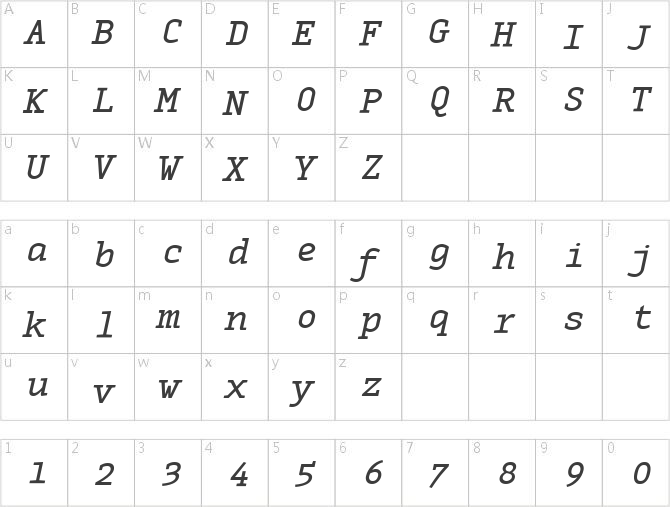
MonoxSerifRegularItalic
MonoxSerifRegularItalic介绍
MonoxSerifRegularItalic字体字库是一款让人赏心悦目、百看不厌的英文字体,适合各类广告和产品包装设计应用,字体大小0.04MB,格式为ttf字体,上传用户是sygyve520,作者/版权方为未知